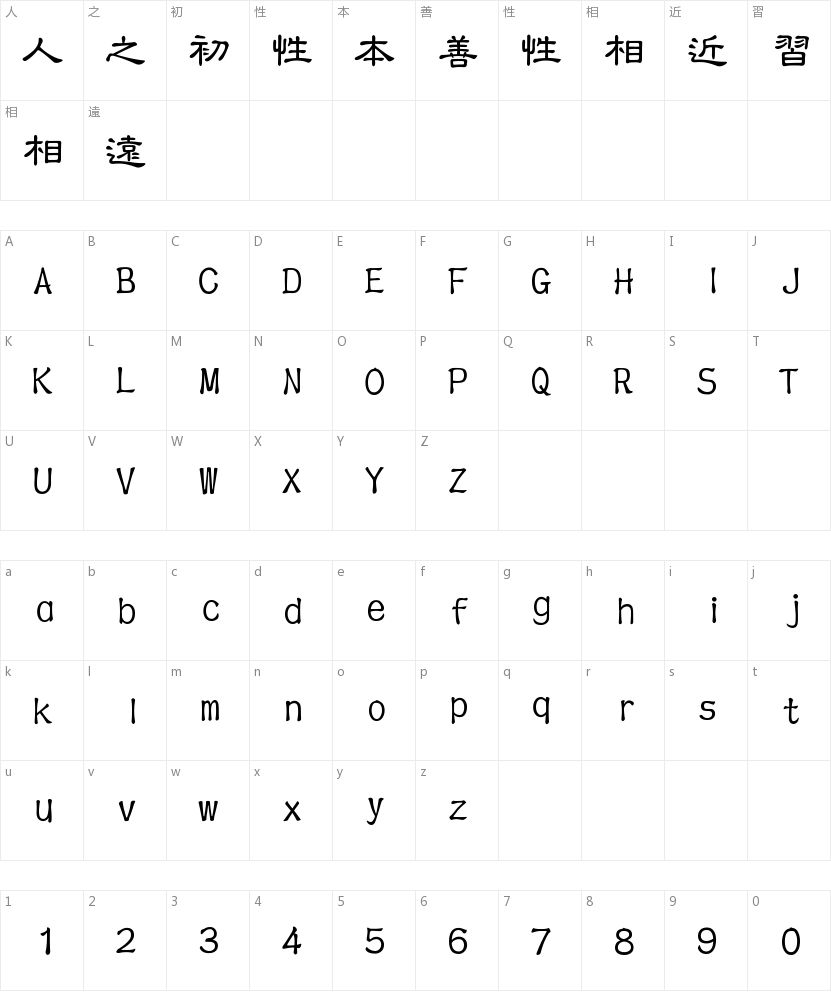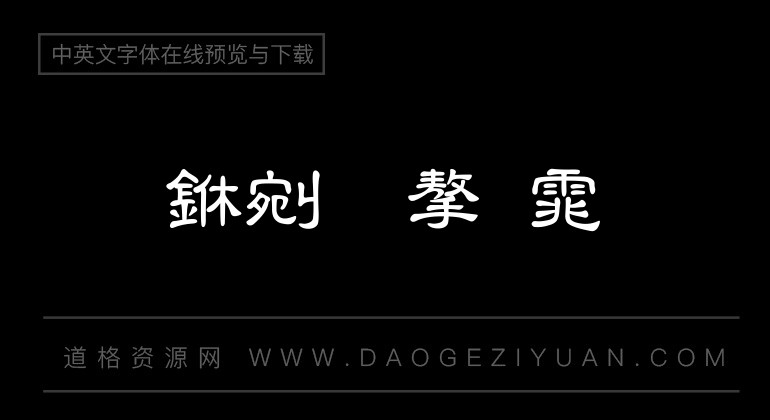
文鼎中粗隶
文鼎中粗隶是一款中国古代书法字体,它由明朝晚期书法家董其昌所创,以“犀利、秀丽、大气、挺拔”的特点而闻名。文鼎中粗隶的笔画比较流畅,线条粗细均匀,笔画间距较大,比较宽松,结构较为简单,易于书写,常被用于写书法、绘画等。
文鼎中粗隶是一款非常不错的手写艺术字体,具有很好的视觉感,适合于文化类的宣传设计、商业类品牌的广告和产品包装设计以及个性化文字排版等较多场景。